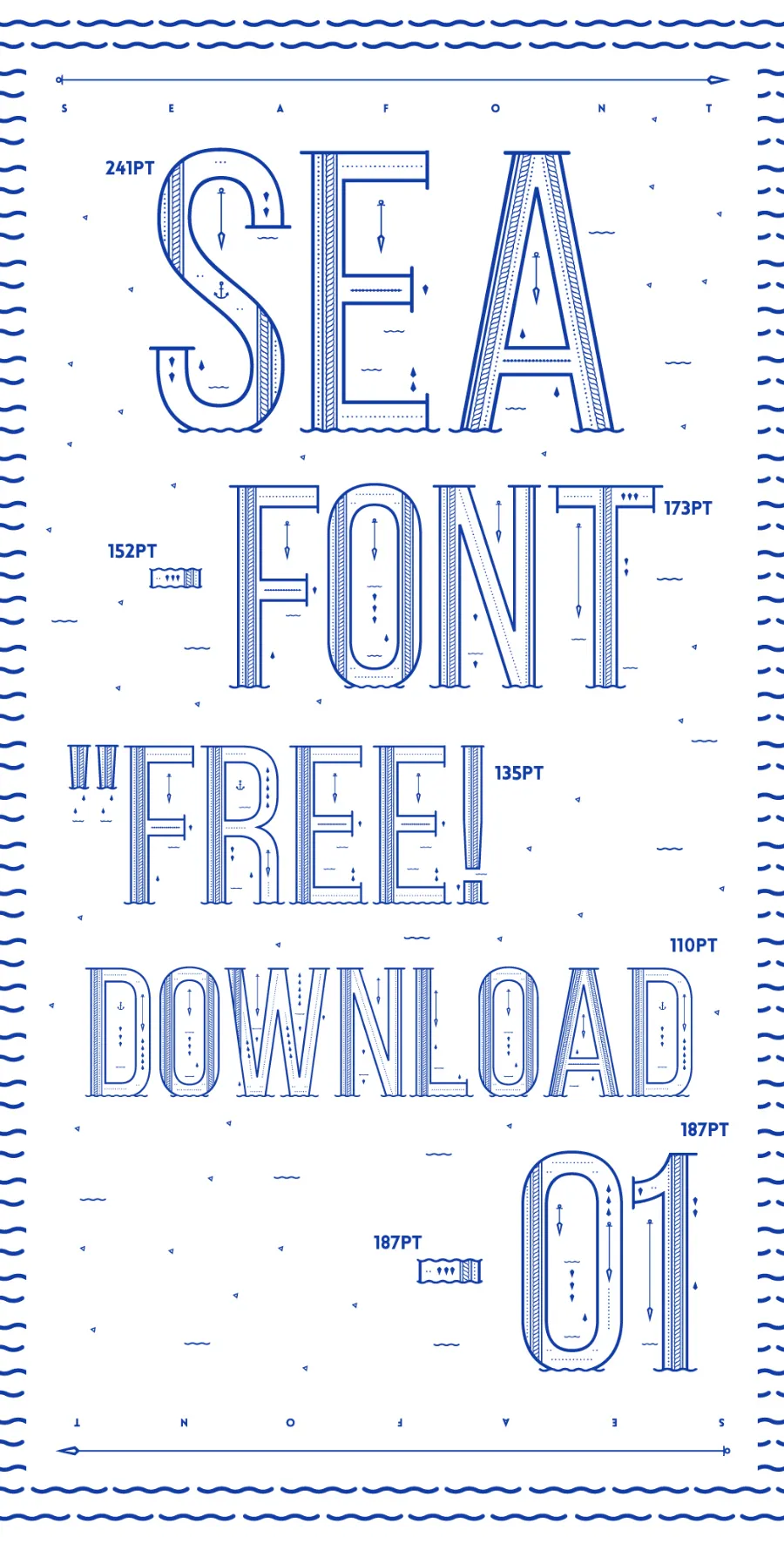
Sea Font – Download Grátis
Aqui está uma versão suave e natural dos dois parágrafos curtos para a descrição do download da font ‘Sea Font’, mantendo-se fiel ao conteúdo original, mas adaptando-o de maneira envolvente: Afonte Sea Font é um design elegante e sofisticado que oferece uma sensação de natureza. Embora seja categorizada como serif fonts, sua forma delicada e delicada se assemelha a folhas flutuantes na água, criando um contraste harmonioso entre a caligrafia clássica e o elemento natural. O designer Hamilton traz uma paleta de texturas suaves ao design, fazendo dela uma escolha perfeita para projetos que valorizam tanto a elegância quanto a sensação de liberdade da natureza. Com um toque suave e harmonioso, Sea Font oferece beleza não apenas aos documentos digitais, mas também às telas gráficas, encorajando os criativos a explorarem a sua versatilidade com uma riqueza de detalhes que reflete o equilíbrio perfeito entre o elegante e o natural.